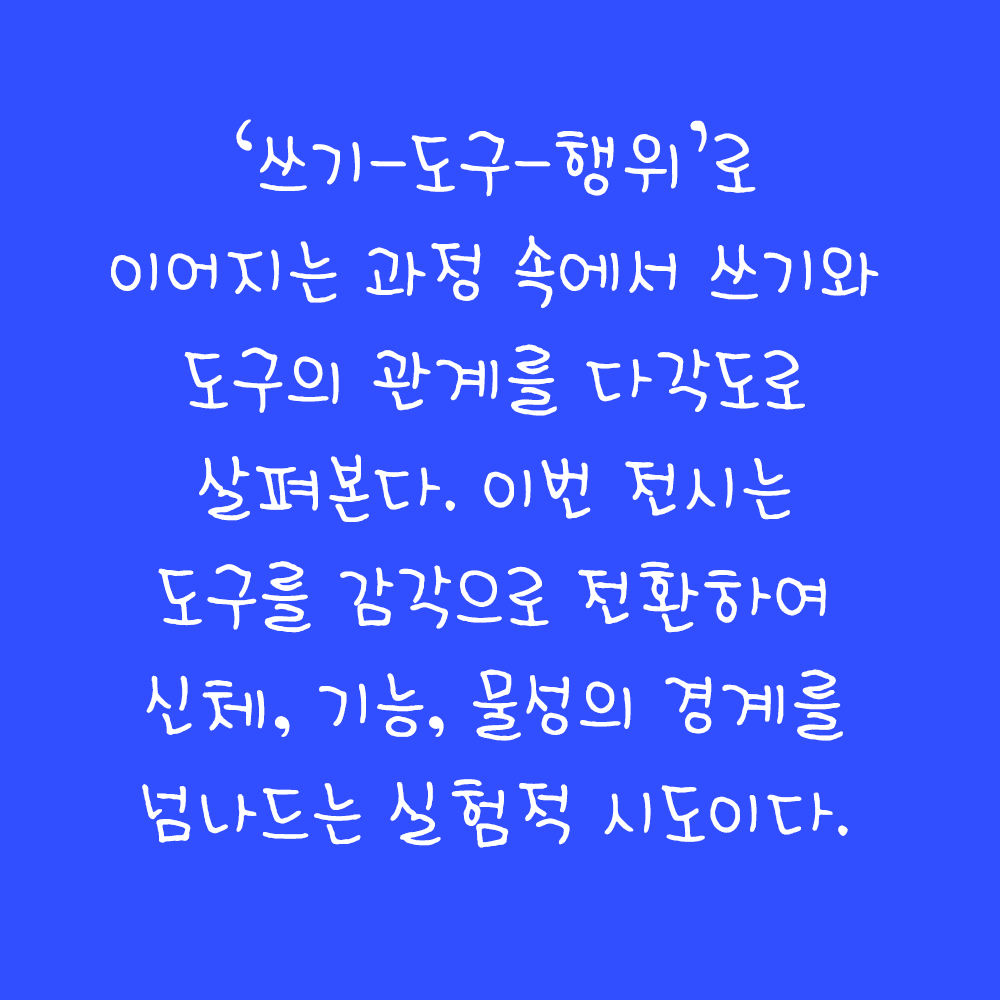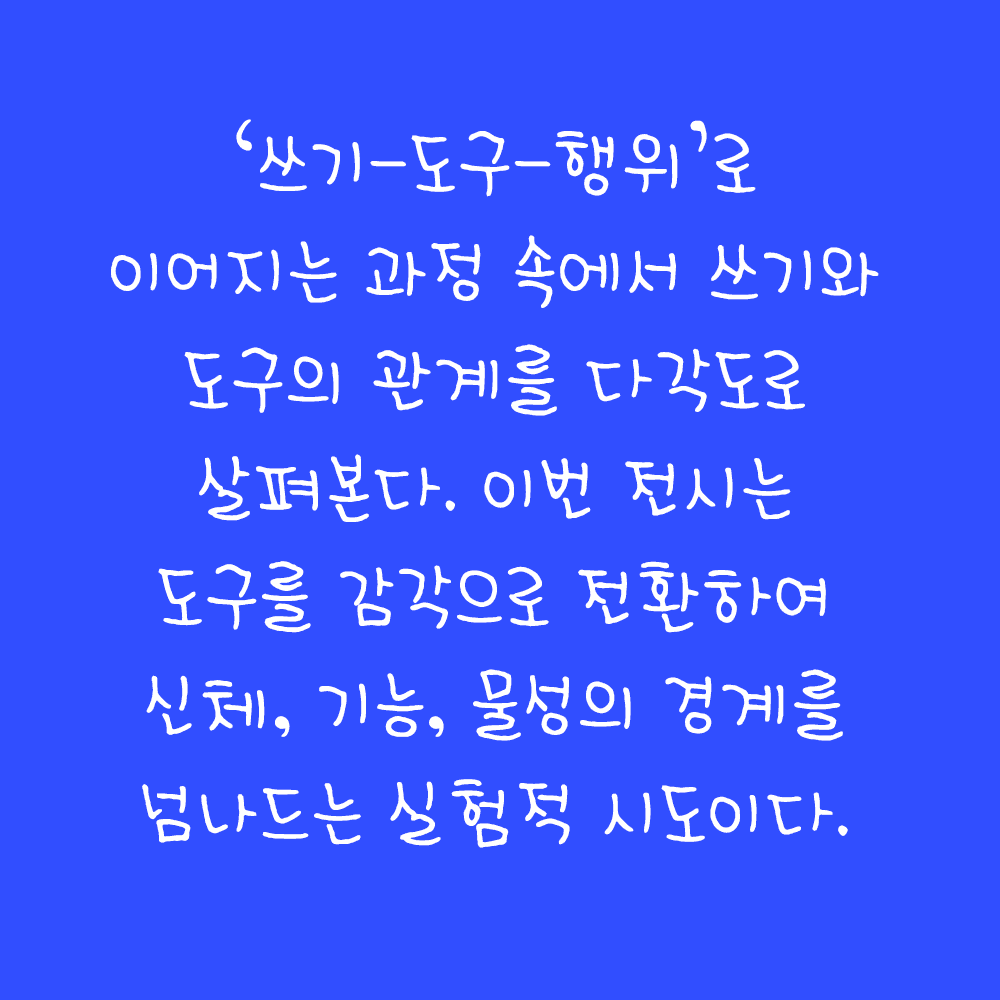
그리운X국한박 권찬욱 떨림체
GriunXHangeul CW's Handwriting
그리운X국한박 권찬욱 떨림체 소개
제5회 한글실험프로젝트 《글(자)감(각): 쓰기와 도구》 The 5th Hangeul Design Project 《Senses of Writing: Tools & Perception》 전시기간: 2025.11.19.~2026.3.22. 전시장소: 문화역서울284 RTO 주최·주관: 국립한글박물관 이 손글씨 폰트는 국립한글박물관 제5회 한글실험프로젝트 《글(자)감(각): 쓰기와 도구》 전시 연계 이벤트를 통해 제작되었습니다. 손의 움직임과 쓰는 감각을 그대로 담아, 쓰기의 경험을 폰트로 확장합니다.